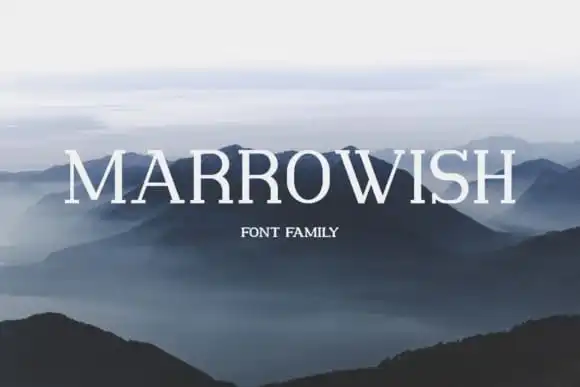
A fonte Marrowish Slab Serif é uma criação especializada para a marca ou design visível que irá impressionar os olhos do público. Ela traz à tona um conjunto de duas coleções, oferecendo tudo o que você precisará para um projeto bem-sucedido. Esta fonte é uma serifada slab criada pelo designer Abdurrasyidismail, com uma aparência encantadora e organizada dos caracteres. Embora possa parecer simples ou básica, a Marrowish Slab Serif é de fato um tipo incrívelmente elegante e adequado tanto para designs formais quanto não-formais. Escolha Marrowish Slab Serif quando deseja dar uma sensação única e marcante ao seu design.